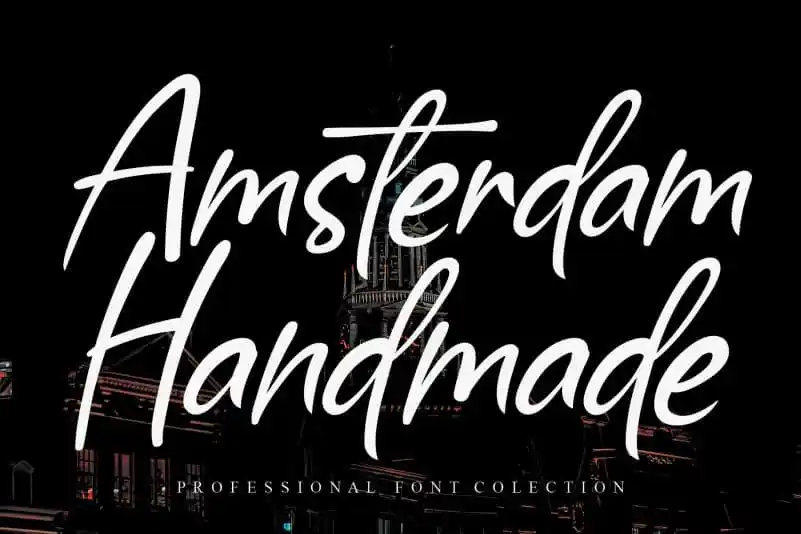
Amsterdam Handmade Script Font – Fonte Grátis
Amsterdam Handmade Script Font
A Amsterdam Handmade Script Font é uma fonte escrita a mão criada pelo designer andikastudio. Este recurso único oferece aos usuários um toque especial e personalizado que irá transformar qualquer projeto de design em algo extraordinário. Com seu estilo elegante e versátil, esta fonte não apenas adicionará um charme único ao seu trabalho de desenho, mas também dará vida a textos e logotipos com uma escrita quase autêntica feita à mão. Seja para aplicativos profissionais ou projetos pessoais, Amsterdam Handmade Script é perfeito para quem busca personalidade e criatividade em cada projeto de design.